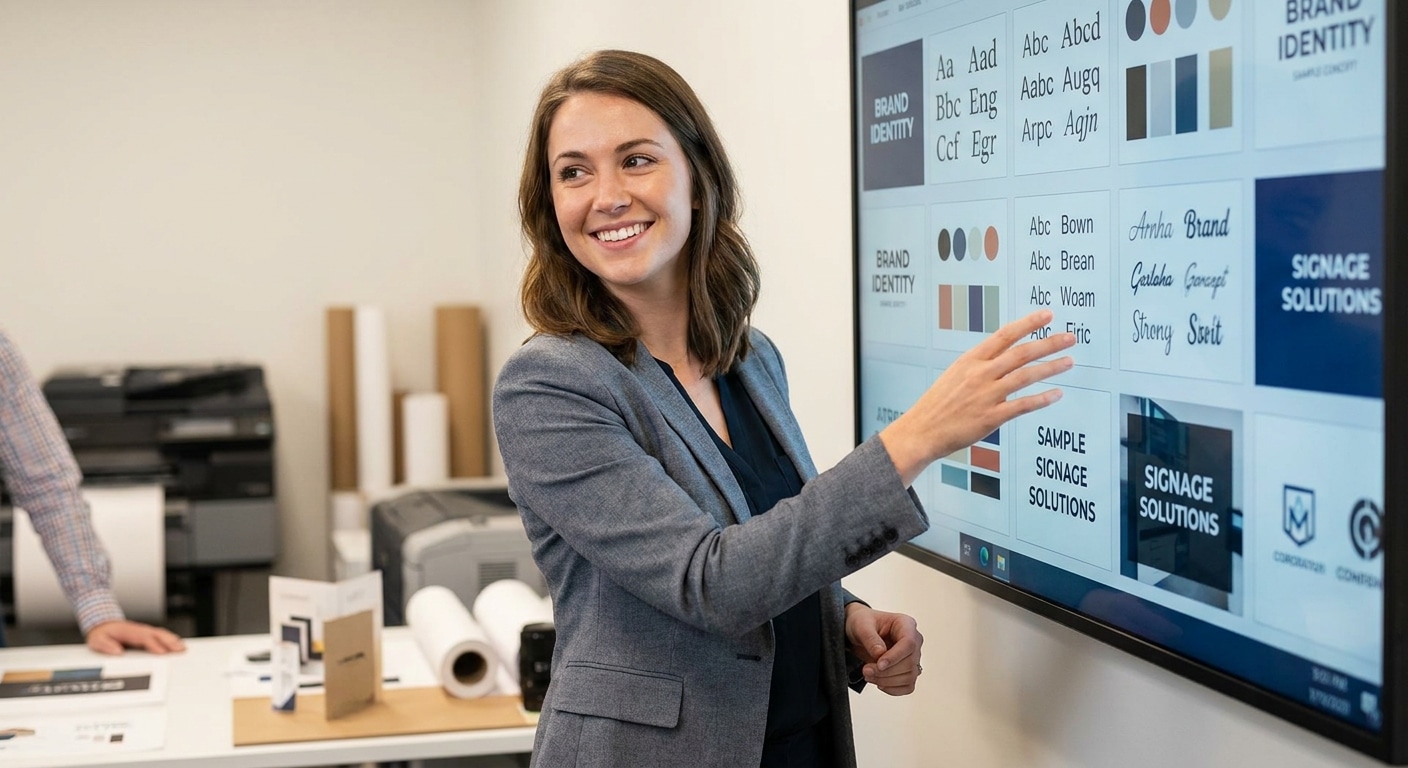
เทคนิคเลือกฟอนต์ทำป้ายและนามบัตร ให้อ่านง่าย ดึงดูดลูกค้า
การเลือกฟอนต์เป็นองค์ประกอบสำคัญในการออกแบบสื่อสิ่งพิมพ์ ที่ส่งผลโดยตรงต่อการรับรู้ของลูกค้าและภาพลักษณ์ของแบรนด์ ตั้งแต่ป้ายโฆษณาขนาดใหญ่ไปจนถึงนามบัตรขนาดเล็ก
- ความชัดเจนในการอ่าน (Legibility และ Readability) คือปัจจัยแรกที่ต้องคำนึงถึง เพื่อให้สารที่ต้องการสื่อไปถึงกลุ่มเป้าหมายได้อย่างถูกต้อง
- ฟอนต์ที่เลือกใช้ต้องสอดคล้องกับบุคลิกของแบรนด์ (Brand Personality) และกลุ่มลูกค้าเป้าหมาย เพื่อสร้างการจดจำและความน่าเชื่อถือ
- การจำกัดจำนวนฟอนต์ในงานออกแบบหนึ่งชิ้น (ไม่เกิน 2-3 รูปแบบ) ช่วยสร้างความเป็นระเบียบและความเป็นมืออาชีพ
- ขนาด น้ำหนัก และการจัดช่องไฟของตัวอักษร เป็นรายละเอียดที่มีผลต่อการรับรู้และความสวยงามไม่น้อยไปกว่าการเลือกรูปแบบฟอนต์
- การเลือกใช้ฟอนต์ต้องคำนึงถึงบริบทของสื่อแต่ละประเภท เช่น ป้ายโฆษณาต้องอ่านง่ายจากระยะไกล ในขณะที่นามบัตรต้องชัดเจนแม้มีขนาดเล็ก
การเรียนรู้เกี่ยวกับเทคนิคเลือกฟอนต์ทำป้ายและนามบัตร ให้อ่านง่าย ดึงดูดลูกค้า ถือเป็นรากฐานสำคัญสำหรับผู้ประกอบการและนักออกแบบทุกคน เพราะฟอนต์ไม่ใช่เพียงแค่ตัวอักษร แต่เป็นเครื่องมือสื่อสารที่ทรงพลังในการสร้างความประทับใจแรกพบและบ่งบอกถึงความเป็นมืออาชีพของธุรกิจ การเลือกฟอนต์ที่เหมาะสมสามารถเปลี่ยนสื่อสิ่งพิมพ์ธรรมดาให้กลายเป็นเครื่องมือทางการตลาดที่มีประสิทธิภาพ ช่วยดึงดูดสายตา สร้างการจดจำ และกระตุ้นการตัดสินใจของลูกค้าได้ในที่สุด
หัวใจสำคัญของการออกแบบ: ทำไมฟอนต์ถึงมีความสำคัญ
ในโลกของการสื่อสารด้วยภาพ ฟอนต์ (Font) หรือรูปแบบตัวอักษร ทำหน้าที่เป็นมากกว่าการเรียงร้อยถ้อยคำให้เป็นประโยค มันคือ “น้ำเสียง” ของแบรนด์ที่สื่อสารกับลูกค้าโดยไม่ต้องเอ่ยคำพูด การเลือกฟอนต์ที่เหมาะสมเป็นสิ่งจำเป็นสำหรับเจ้าของธุรกิจ นักการตลาด และนักออกแบบที่ต้องการสร้างสื่อที่มีประสิทธิภาพ ไม่ว่าจะเป็นการทำป้ายโฆษณาที่ต้องดึงดูดความสนใจในเสี้ยววินาที หรือการออกแบบนามบัตรที่ต้องสร้างความน่าเชื่อถือและน่าจดจำ
ความสำคัญของฟอนต์อยู่ที่ความสามารถในการกำหนดอารมณ์และความรู้สึกของผู้อ่าน ฟอนต์ที่ดูแข็งแรงและมั่นคงอาจสื่อถึงความน่าเชื่อถือและความเป็นทางการ เหมาะสำหรับธุรกิจกฎหมายหรือสถาบันการเงิน ในขณะที่ฟอนต์ที่ดูสนุกสนานและเป็นกันเองอาจเหมาะกับร้านกาแฟหรือสินค้าสำหรับเด็ก ดังนั้น การทำความเข้าใจในหลักการเลือกฟอนต์จึงไม่ใช่แค่เรื่องของความสวยงาม แต่เป็นกลยุทธ์ที่ส่งผลโดยตรงต่อการรับรู้และภาพลักษณ์ของแบรนด์ในใจของผู้บริโภค
หลักการพื้นฐานเพื่อการสื่อสารที่ชัดเจน
ก่อนที่จะลงลึกในเทคนิคการเลือกฟอนต์ สิ่งสำคัญคือการทำความเข้าใจหลักการพื้นฐานที่ทำให้ตัวอักษรสามารถทำหน้าที่สื่อสารได้อย่างมีประสิทธิภาพสูงสุด ซึ่งประกอบด้วยความสามารถในการอ่านและประเภทของฟอนต์ที่เป็นที่นิยม
ความสามารถในการอ่าน (Legibility & Readability)
แม้จะฟังดูคล้ายกัน แต่คำสองคำนี้มีความหมายที่แตกต่างและสำคัญอย่างยิ่งในการออกแบบ:
- Legibility (ความชัดเจนของตัวอักษร): หมายถึงความง่ายในการแยกแยะตัวอักษรแต่ละตัวออกจากกัน เช่น การแยกความแตกต่างระหว่าง ‘ก’ กับ ‘ถ’ หรือ ‘O’ กับ ‘Q’ ฟอนต์ที่มี Legibility สูงจะมีรูปทรงของตัวอักษรที่ชัดเจน ไม่ซับซ้อน และไม่มีส่วนตกแต่งที่รบกวนสายตามากเกินไป
- Readability (ความง่ายในการอ่านข้อความ): หมายถึงความสะดวกสบายในการอ่านข้อความหรือย่อหน้ายาวๆ โดยไม่รู้สึกเมื่อยล้าสายตา ปัจจัยที่ส่งผลต่อ Readability ได้แก่ การเลือกใช้ฟอนต์ การจัดขนาดตัวอักษร ความยาวของบรรทัด และระยะห่างระหว่างบรรทัด (Leading) ฟอนต์ที่มี Readability ดีจะช่วยให้ผู้อ่านติดตามเนื้อหาได้อย่างลื่นไหล
ในการออกแบบป้ายและนามบัตร ทั้ง Legibility และ Readability มีความสำคัญเท่าเทียมกัน ป้ายโฆษณาต้องการ Legibility สูงสุดเพื่อให้มองเห็นและเข้าใจได้ทันทีจากระยะไกล ส่วนนามบัตรต้องการ Readability ที่ดีเพื่อให้ข้อมูลติดต่อสามารถอ่านได้อย่างง่ายดายในระยะใกล้
ประเภทฟอนต์หลัก: Serif และ Sans-serif
ฟอนต์ส่วนใหญ่ในโลกสามารถแบ่งออกเป็นสองประเภทหลัก ซึ่งแต่ละประเภทมีลักษณะและให้ความรู้สึกที่แตกต่างกัน:
ฟอนต์ Serif (มีเชิง/มีหัว)
ฟอนต์ประเภทนี้มีลักษณะเด่นคือมี “เชิง” หรือ “ขีดเล็กๆ” อยู่ที่ปลายของเส้นตัวอักษร (เช่น Times New Roman, Garamond) เชิงเหล่านี้ช่วยนำสายตาของผู้อ่านไปตามบรรทัด ทำให้เหมาะสำหรับเนื้อหาขนาดยาวในสื่อสิ่งพิมพ์ เช่น หนังสือหรือนิตยสาร ฟอนต์ Serif มักให้ความรู้สึกคลาสสิก เป็นทางการ น่าเชื่อถือ และสง่างาม
ฟอนต์ Sans-serif (ไม่มีเชิง/ไม่มีหัว)
“Sans” เป็นคำภาษาฝรั่งเศสที่แปลว่า “ไม่มี” ดังนั้น Sans-serif จึงหมายถึงฟอนต์ที่ไม่มีเชิงที่ปลายตัวอักษร ทำให้มีรูปลักษณ์ที่ดูสะอาดตา เรียบง่าย และทันสมัย (เช่น Helvetica, Arial, Kanit) ด้วยความชัดเจนและเรียบง่าย ฟอนต์ประเภทนี้จึงเป็นที่นิยมอย่างมากสำหรับพาดหัวข่าว ป้ายต่างๆ และการแสดงผลบนหน้าจอดิจิทัลที่ความละเอียดต่ำอาจทำให้เชิงของฟอนต์ Serif ดูไม่คมชัด
| คุณลักษณะ | ฟอนต์ Serif (มีเชิง) | ฟอนต์ Sans-serif (ไม่มีเชิง) |
| ลักษณะเด่น | มีขีดเล็กๆ ที่ปลายตัวอักษร | ไม่มีขีดที่ปลายตัวอักษร เส้นเรียบ |
| ภาพลักษณ์/อารมณ์ | คลาสสิก, เป็นทางการ, น่าเชื่อถือ, สง่างาม | ทันสมัย, เรียบง่าย, เป็นมิตร, ชัดเจน |
| การใช้งานที่เหมาะสม | เนื้อหายาวๆ ในสื่อสิ่งพิมพ์, โลโก้แบรนด์ที่เน้นความดั้งเดิม, นามบัตรสำหรับวิชาชีพที่ต้องการความน่าเชื่อถือ | พาดหัว, ป้ายโฆษณา, เว็บไซต์และแอปพลิเคชัน, นามบัตรสำหรับธุรกิจสตาร์ทอัพหรือเทคโนโลยี |
| ตัวอย่างฟอนต์ | Times New Roman, Garamond, Bodoni | Helvetica, Arial, Montserrat, Kanit, Prompt |
องค์ประกอบที่ส่งผลต่อการอ่าน
นอกจากการเลือกประเภทฟอนต์แล้ว รายละเอียดเล็กๆ น้อยๆ ต่อไปนี้ยังมีผลอย่างมากต่อความสามารถในการอ่าน: